Web Sitesi İçin Doğru Yazı Tiplerini Seçme - Bir Kılavuz
İnsanların hayatımızın neredeyse her yönü için tekrar ettiğini ve başvurduğunu duyduğumuz bir şey. Web sitelerimizi de içerir.
Bir SaaS veya E-ticaret markası olmanız farketmez, ancak bir ziyaretçi web sitenizi ilk ziyaret ettiğinde fark ettiği ilk özellik sayfa düzeni ve yazı tipidir. Bu nedenle, web sitenizi tasarlarken tam anlamıyla isabetli olmanız sizin için çok önemli hale geliyor.
Tasarım, birbiriyle uyumlu çalışan bir dizi yönü kapsadığı için yoğun ve hantal bir iştir.
Bazı insanlar Google yazı tiplerini tercih ederken, diğerleri tipografi veya el yazısı kullanmayı tercih edebilir. Ancak çalışıp çalışmadığı, tasarım sürecinde yer alan diğer faktörlere bağlıdır. Navigasyon, yazı tipi, düzen, renk şeması, okunabilirlik ve çok daha fazlasına sahipsiniz.
Yazı tiplerine gelince, bir web sayfasında her yerde bulunurlar. Bunları başlıklar, gövde metinleri ve diğer her yerde bulacaksınız. Bu nedenle, doğru yazı tiplerini seçmek, genel web sitenizin görünümünden yararlanabilir.
Bugün, web siteleri için yazı tiplerini nasıl seçmeniz gerektiğini tartışacağız.
Bir Web Sitesi İçin En İyi Yazı Tiplerini Seçmenin Önemi
Yazı tipiniz marka elçinizdir
Ziyaretçinizin web siteniz ve yazı tipi seçimleriniz hakkında olumlu bir fikre sahip olmasını sağlamak için sadece 0,5 saniyeniz var. Çoğunluğu, %94'ü tasarım öğelerine bağlıdır.
Her yazı tipinin benzersiz bir dizi özellik ile geldiğini anlamak zorunludur. Bu nedenle, ziyaretçileri uzmanlığınız konusunda ikna etmek istiyorsanız, bunu web sitesinin tasarım dili ve yazı tipi seçimi ile yapmanız önemli hale gelir.
Genel kullanıcı deneyimini artırmaya yardımcı olur
Neden bir web sitesi oluşturmak için zaman ve kaynak harcıyoruz? Çünkü ziyaretçilerimizin onu kullanırken rahat etmelerini istiyoruz.
Kusursuz bir kullanıcı deneyimi oluşturmak, ayrıntılar için keskin bir göze sahip olmanızı gerektirecektir. Aynı zamanda, ziyaretçilerinizin yerine geçmek ve belirli bir tasarım seçiminin onlar için işe yarayıp yaramadığını ölçmek anlamına gelir.
Web tasarımı için iyi yazı tiplerini seçmek, hepsinin ayrılmaz bir parçasıdır. Daha fazla ziyaretçi, daha yüksek dönüşüm ve daha iyi genel memnuniyet oluşturmanıza yardımcı olabilir.
Web Sayfası için Yazı Tiplerinin Sınıflandırılması
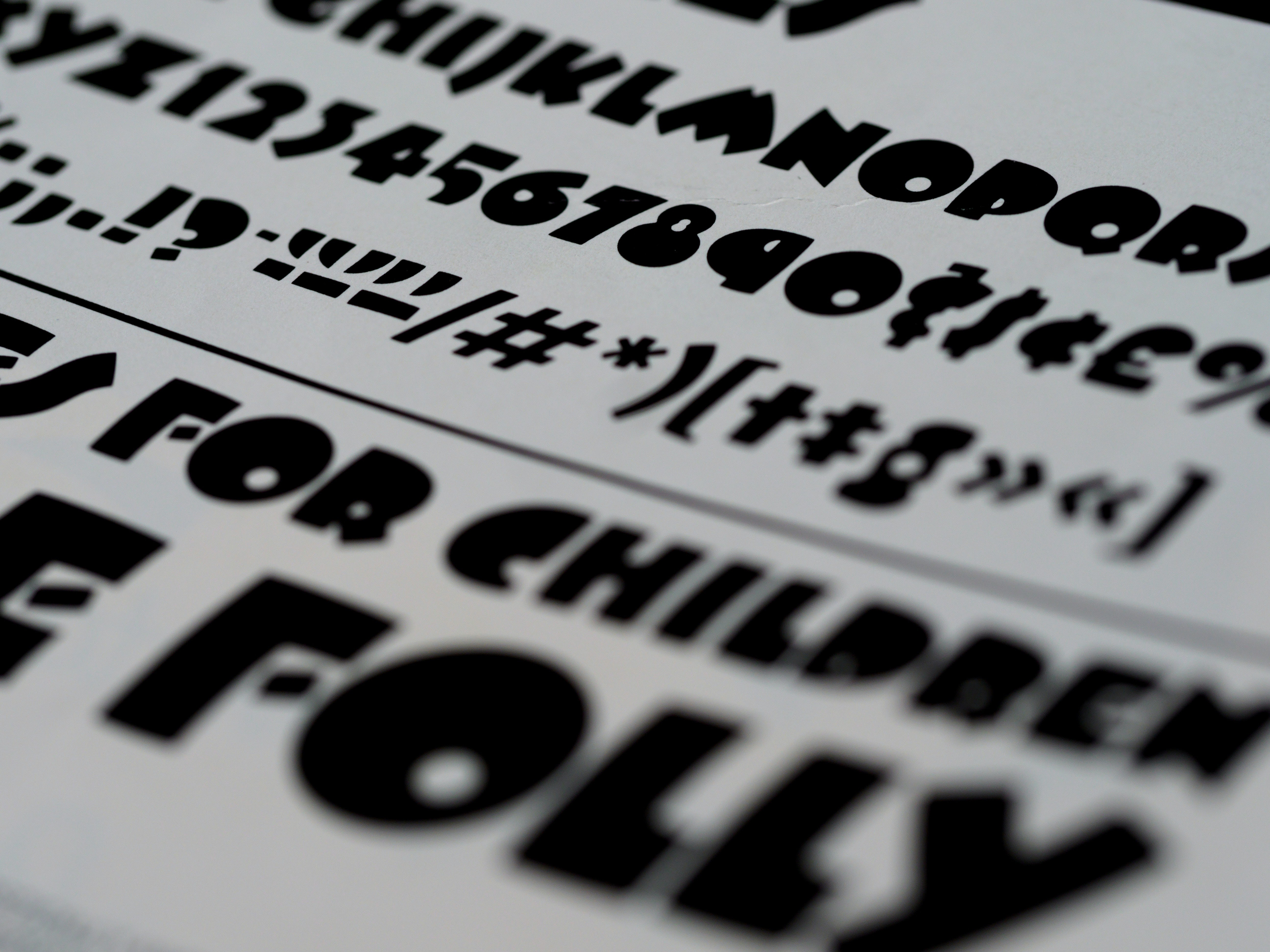
Her yazı tipi stilinin kendi hikayesi ve özellikleri olduğundan daha önce bahsetmiştik, yani onları birkaç gruba ayırabilirsiniz. Ayrıca, seçim yapabileceğiniz ve web sayfanıza ekleyebileceğiniz çok sayıda ücretli ve ücretsiz yazı tipi vardır.
Web sitesi yazı tiplerini aşağıdaki kategorilere ayırabiliriz:
şerif
Örnekler – Times New Roman, Garamond, MS Serif, Merriweather, Abril Fatface, Playfair Display, Georgia
Serif yazı tipleri, insanlar tarafından bilinen en eski yazı tiplerinden biridir. Rönesans'tan ilham alan yazı tipleri, eski günlerde yüksek okunabilirlikleriyle ünlüydü.
Günümüz Serif yazı tipleri, dijital olarak da olsa aynı mirası taşır. Enine veya çapraz çizgi sonlarını fark ederek bunları tanıyabilirsiniz. Tasarım diline zarafet katar ve onu kitaplar ve resmi web siteleri için mükemmel bir seçim haline getirir.
Çoğu tasarımcı, bu yazı tiplerini ek içerik öğeleri veya web sayfalarında görünenler için kullanır. Bu yüzden onları başlıklar, alt yazılar, logolar ve benzeri metinler olarak bulmanız daha olasıdır.
Sans Serif
Örnekler – Arial, Alegreya, Open Sans, Montserrat, Comic Sans, Verdana, Oswald, Roboto, Lato, Helvetica
Sans-serif yazı tipleri, Serif'in modern yinelemesidir. Adından da anlaşılacağı gibi, bunlar serif olmadan gelir ve minimalist bir his uyandırır. İlk günlerde, bilgisayar ekranları serifleri orijinal biçimleriyle sunacak kadar gelişmiş değildi. Böylece tasarımcılar, dijital okuma için daha uygun olan yazı tiplerini keşfettiler.
Sans-serif ayrıca okuyucuyu yormaz ve daha geniş bir kitleye hitap ederek tasarımcılara esneklik sunar. Bu yazı tiplerinin en yaygın kullanıcıları genç nesle hitap ediyor ve yaklaşımlarında modern ve profesyonel olarak algılanmak istiyor.
Varsayılan Windows işletim sistemi yazı tipi olan Segoe UI, bir Sans-serif yazı tipi stilidir. Base 9 & 12, muhtemelen karşılaşabileceğiniz en popüler Adobe font türlerinden biridir ve Sans-serif kategorisine aittir. Apple platformundaki en popüler yazı karakterlerinden biri olan SF Pro da bu kategoriye giriyor.
levha serif
Örnekler - Sentinel, Clarendon, Adelle, Arvo
Mısır yazı tipi olarak Slab Serif olarak da bilinen bir Serif yazı tipi. Bunlar, geleneksel Serif'ten daha düşük kontrast oranına sahip bloklu ve sağlam görünümlü yazı tipi stilleridir.
Seçtiğiniz yazı tipi stiline bağlı olarak, bunlar eski tarz retrodan daha çağdaş bir görünüme kadar değişebilir. Genellikle, Slab Serif'i ekran metninin bir parçası olarak bulacaksınız, ancak bunlar gövde metnini ayarlamak için de kullanılabilir.
Senaryo
Örnekler – Arizona, Mandalina, Great Vibes
Adından da anlaşılacağı gibi, betik yazı tipleri insan el yazısına en yakın şeydir. Süslüdürler ve genellikle onları web sitesinin başlıklarını, logolarını ve benzeri kısa cümleleri süslerken bulacaksınız.
Ayrıca, bunlar gayri resmi olarak kabul edilebilir. Komut dosyası yazı tipleriyle ilgili en heyecan verici gerçek, yüksek duygusal yükleridir. Bunlar bir tepki uyandırabilir (çoğu durumda spesifiktir) ve ziyaretçilerin çok ilgisini çekebilir.
Karmaşıklıkları göz önüne alındığında, sınırlı kullanımları vardır. Bununla birlikte, iyi tasarlanmış web sitelerinin çoğu, genel hissi artırmak için bunları kullanır.
Dekoratif
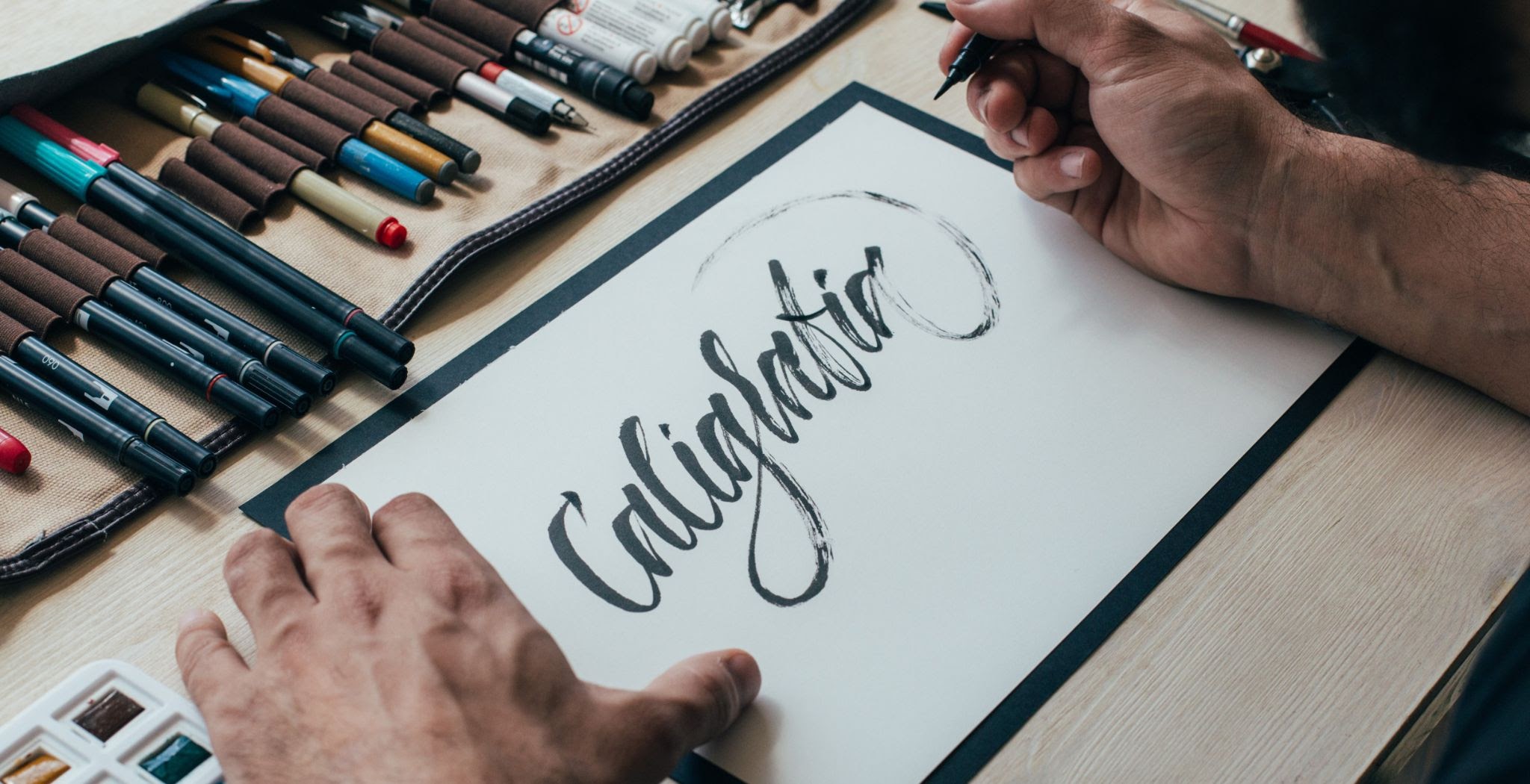
Örnek – Helios, Casandra, Cherie Bomb, Kırsal
Ekran yazı tipleri olarak da bilinen dekoratif yazı tipleri, mutlaka ortak özellikleri paylaşmayan çeşitli yazı tiplerini ifade eder. Onları tanımlamanın tek ortak yolu, ayrıntılı şekillerini ve yüksek süslemelerini fark etmektir.
Bunlar 19. yüzyılda popüler hale geldi ve o zamandan beri web tasarımı ve reklam amaçları için sabit oldu.
Farklı durumlarda kendilerini özümseyebilen diğer yazı tiplerinin aksine, dekoratif yazı tiplerinin sınırlamaları vardır, yani her biri belirli duygular (mutluluk, korku veya başka herhangi bir şey) yayar. Bunlar, son derece etkileyici ve kolayca tanınabilen orijinal yazı tipleridir.
Bunlar, yalnızca başlıklarda kullanabileceğiniz kalın yazı tipleridir ve bunları web sitenizin gövde metni için kullanmamanızı öneririz. Web tasarımı için bunları minimalist bir şekilde özümsemek, web sitesinin öne çıkmasını ve ziyaretçiler üzerinde kalıcı bir izlenim bırakmasını sağlayacaktır.
Yazı Tipi ve Yazı Tipi Arasındaki Fark
Genel fikir, yazı tipi ve yazı tipinin aynı anlama sahip olduğu, ancak bunların eşanlamlı olmadığıdır. İlki, ortak özelliklere ve özelliklere sahip bir yazı tipi ailesini ifade ederken, ikincisi tek bir yazı tipini ifade eder.
Örneğin, Arial bir yazı tipidir ve 16pt Arial Bold bir yazı tipidir.
Bir Web Sitesi İçin Varsayılan Yazı Tiplerini Seçerken Akılda Tutulması Gerekenler
Dünyada çok sayıda kusursuz ücretli ve ücretsiz yazı tipi olduğunu biliyoruz. Ancak web sitesini tasarlarken oynanacak daha birçok şey var ve sevdiğiniz birini seçemezsiniz. Web siteleri için en iyi yazı tipini seçmek bütünsel bir iştir ve oyundaki diğer unsurların kapsamlı bir şekilde araştırılmasını ve anlaşılmasını gerektirir.
Bir web sitesi için en iyi yazı tiplerini seçerken göz önünde bulundurmanız gereken şeyler:
Temel bilgileri doğru alın
Web siteleri için iyi yazı tipleri aramadan önce, ilgili diğer şeyleri sıralamanız gerekir. Bunlar;
- Hedef kitlenizi anlamak
- web sitesinin amacı
- Markanızın varlık nedeni
- Taşıdığı kişilik
Amazon gibi bir marka Horror yazı tipi kullanmayacaktır (Cadılar Bayramı gibi belirli durumlar dışında). Kullandığınız yazı tipi türü, temel olarak hedef kitlenize ve oluşturmak istediğiniz duygulara bağlıdır.
Örneğin – Sans-serif yazı tipleri minimalizm ve sadeliği ifade eder. Ayrıca geleneksel değerlere ve esnekliğe olan eğiliminizi de beraberinde getirirler. Serif yazı tipleri, resmi temsil eden dekoratif bir kontura sahiptir.
Seçiminizin tasarım amacınızla uyumlu olduğundan emin olun.
Her şeyin arkasında bir amaç vardır ve web sitesi tasarımınızın da bir amacı vardır. Seçiminiz nihayetinde hedef kitlenize ve web siteniz aracılığıyla uyandırmak istediğiniz genel ruh haline bağlı olacaktır. Ayrıca, birkaç tasarım öğesi, web sayfalarınızın genel sunumunda hayati bir rol oynar.
İşte aklınızda bulundurmanız gereken unsurlar –
Karakter aralığı, yönlendirme ve izleme
Bu üç terim, bir web sitesindeki boşluk öğelerini ifade eder. Karakter aralığı, iki bitişik harf arasındaki boşluğu belirtir. Satır aralığı, metin satırları arasındaki boşluğu tanımlar ve harf grupları arasındaki boşluk, izleme olarak bilinir. Seçtiğiniz boşluk, yazı tipinizin görünümünü belirlemenizi sağlar.
Zıtlık
Web siteleri ile ilgili olarak kontrast, metnin sunumuna atıfta bulunur. Web sitesi tasarımcıları, bazı öğeleri öne çıkarmak için bir dizi ince teknik kullanır. Bunlar, kritik alanları güçlendirmek için renk, biçim, boyut, yapı ve ağırlığı içerir.
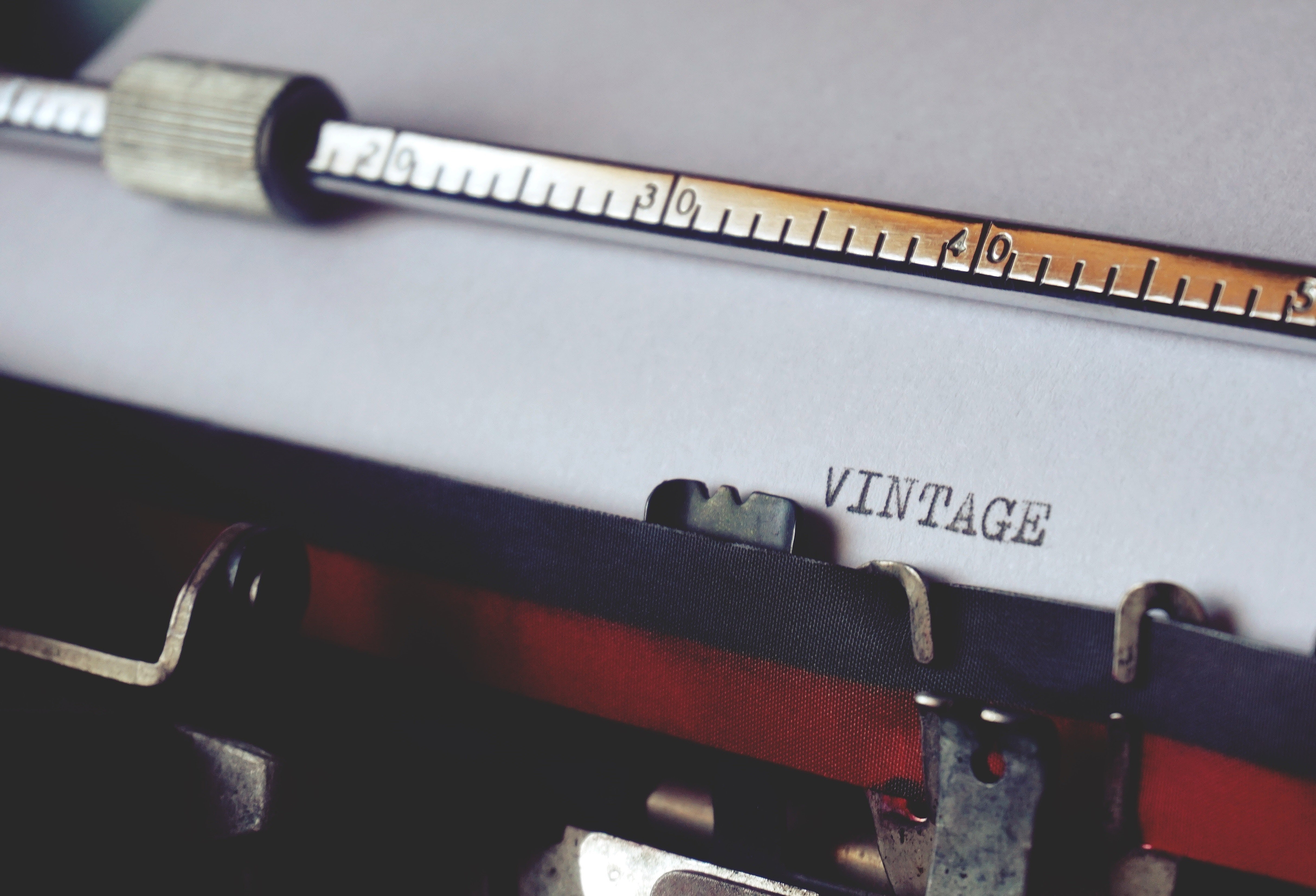
hizalama
Hizalama, metni bir web sitesine yerleştirme şeklinizi ifade eder. Sol, sağ veya orta olabilir. Tam olarak gerekçelendirilmiş bir metin daha resmi bir yaklaşım sunarken, düzensiz yöntem daha resmi olmayan ve arkadaşça olmayı amaçlayan bir web sitesine uygundur.
Genellikle, sola hizalanmış metin en okunaklı olanıdır. Akılda tutulması gereken bir diğer husus, metin bloğunun kenarları arasındaki mesafedir. 80 karaktere kadar (boşluklar dahil) bir ortalama karakter sayısı ayarlayarak en uygun satır uzunluğunu ayarlayabilirsiniz.
Daha resmi bir görünüm arıyorsanız, tam olarak gerekçeli bir metin seçebilirsiniz. Yazı tipini her iki tarafta eşit şekilde hizalar ve yönelim bozukluğu hissini ortadan kaldırır.
Yazı tiplerini akıllıca kullanın
Sunulan çok sayıda yazı tipi ve yazı tipi göz önüne alındığında, tasarım seçimlerinizi yaparken kaybolma olasılığınız yüksek. Bu yüzden bir adım geri atmalı ve yaratmak istediğiniz son ürünü anlamalısınız.
Bir sonraki adım, yazı tipini buna göre biçimlendirmektir. Bu tasarım seçenekleri, hizmet verdiğiniz kitleyi yansıtır ve markanızın yaklaşımına ilişkin temel bir anlayışa hizmet eder.
Bu nedenle, tasarım öğelerini sonlandırırken kendinize aşağıdaki gibi sorular sorun:
- Markanızın doğası nedir?
- Pratikliğe daha fazla önem mi vermek istiyorsunuz yoksa öne mi çıkmak istiyorsunuz?
- Web siteniz ne tür grafikler içerecek? Grafik ağırlıklıysa, ön kısmın sesini kısabilir ve gerisini konuşmaya bırakabilirsiniz. Tam tersi ise, yazı tipi seçiminizin istediğiniz duyguları uyandırdığından emin olun.
- Proje bazlı mı? Evet ise, bu ne tür bir görevdir ve ilgili gereksinimler nelerdir?
Yükleme sürelerini dikkate almayı unutmayın
Yavaş siteler düşük trafiğe eşittir. Pek çoğu, web sitenizin bir öğeyi birbiri ardına yüklemesini bekleyecek bant genişliğine sahip değildir. Tasarım öğelerini yanlış anlamak veya tasarım seçimlerinde aşırıya kaçmak, sitenizin yavaşlamasına ve etkileşiminizin azalmasına neden olabilir.
Yüksek yükleme sürelerinden muzdaripseniz, benimsediğiniz yazı tipi ve stillerin sayısına bakmalısınız. Yalnızca gerekli olanları seçtiğinizden emin olun.
Web uyumlu yazı tiplerini seçin
Web sitesi yazı tiplerinin seçimi genellikle markanızı nasıl tasvir ettiğinizin bir temsilidir. Örneğin, Amazon, Microsoft ve Disney gibi küresel markalar, kendileriyle eş anlamlı hale gelen farklı yazı tiplerini kullanır.
Aynısını kendiniz için yapamasanız bile, seçimlerinizin web için güvenli kabul edildiğinden emin olmanız zorunludur. Terim, farklı ortamlara uyum sağlayabilen bir dizi dinamik yazı tipini temsil eder. Basit bir ifadeyle, bu yazı biçimleri, cihazlarında yüklü olmasalar bile bir okuyucunun ekranında görüntülenebilir.
Bunlardan birini kullanmazsanız, tarayıcı yedek olarak tutulan genel bir yazı tipine döner ve web içeriğinizi bu yazı tipinde görüntüler. İşlevsellik ve tasarım sorunlarına neden olabilir, eksik mesajlaşmaya yol açabilir ve markanıza musallat olabilir.
Birkaç yıl önce, web için güvenli yazı tiplerini bulmak zordu, ancak bugün seçip içebileceğiniz çok sayıda ücretli ve ücretsiz yazı tipi var.
Örneğin, Times New Roman ve Arial, sırasıyla Serif ve Sans-serif kategorilerine ait web uyumlu yazı tipleridir. Dekoratif bir şey arıyorsanız, Script MT ve Luminari sırasıyla Cursive ve Fantasy kategorilerine ait uyarlanabilir yazı tipleridir.
En İyi Sonuçlar İçin Bir Yazı Tipi Karışımı Kullanmanın Zamanı Geldi
Web siteleri için en iyi web yazı tiplerini seçmek, hesaplanmış karıştırma ve eşleştirme ile ilgilidir. Her yazı tipinin kendine has özellikleri olduğu için, sınıfı ve neden var olduğunuzu eninde sonunda yansıtacak şekilde üç adede kadar farklı yazı tipi (birincil, ikincil ve üçüncül) seçmenizi öneririz.
Buna karakter aralığı ve yönlendirme gibi faktörleri ekleyin ve doğru yapmak için çok fazla bacak boşluğunuz var. Bazı yazı tiplerinin çiftler halinde iyi çalıştığını, bazılarının ise çalışmadığını anlamak da çok önemlidir. Dolayısıyla seçenek sıkıntısı yok, ancak bunun markanızın vizyonuyla uyumlu olmasını sağlamanız gerekecek.
Ayrıca günümüzde internet kullanıcılarının dinamik kullanım kalıbı göz önüne alındığında, ekran boyutuna dinamik olarak uyum sağlamak için web uyumlu yazı tiplerinin kullanılması zorunludur. Belirli bir yazı tipi yüklü olmasa bile, son kullanıcıların web sayfasını amaçlandığı gibi görmelerini sağlar.
Sonuç olarak, yazı tipi seçimi birçok faktöre bağlıdır ve en iyi sonuçları elde etmek için doğru dengeyi sağlamanız gerekecektir.